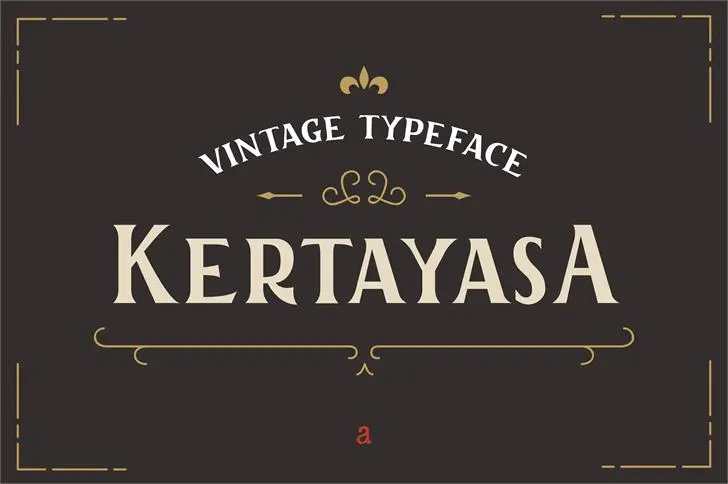
A Kertayasa é uma elegante tipografia vintage que captura a essência do passado, seu nome derivando do Sansekerta, um alfabeto antigamente utilizado na Península Indochina e que possui dignidade e felicidade entre suas significações. Esta fonte retrata um retorno ao estilo das décadas de papagaio dos anos 50 e 60, com seus traços suaves e curvados que transmitem um sentimento nostálgico e sofisticado. Para aqueles que buscam uma alternativa às tipografias modernas, a Kertayasa oferece uma opção para recriar atmosferas mais vintage em seu design web, aplicativos de notícias ou materiais gráficos antigos. Como um designer retro apreciador, Hamilton criou esta fonte perfeita para quem busca trazer o charme das décadas ao seu trabalho, seja em uma página pessoal ou de negócios.